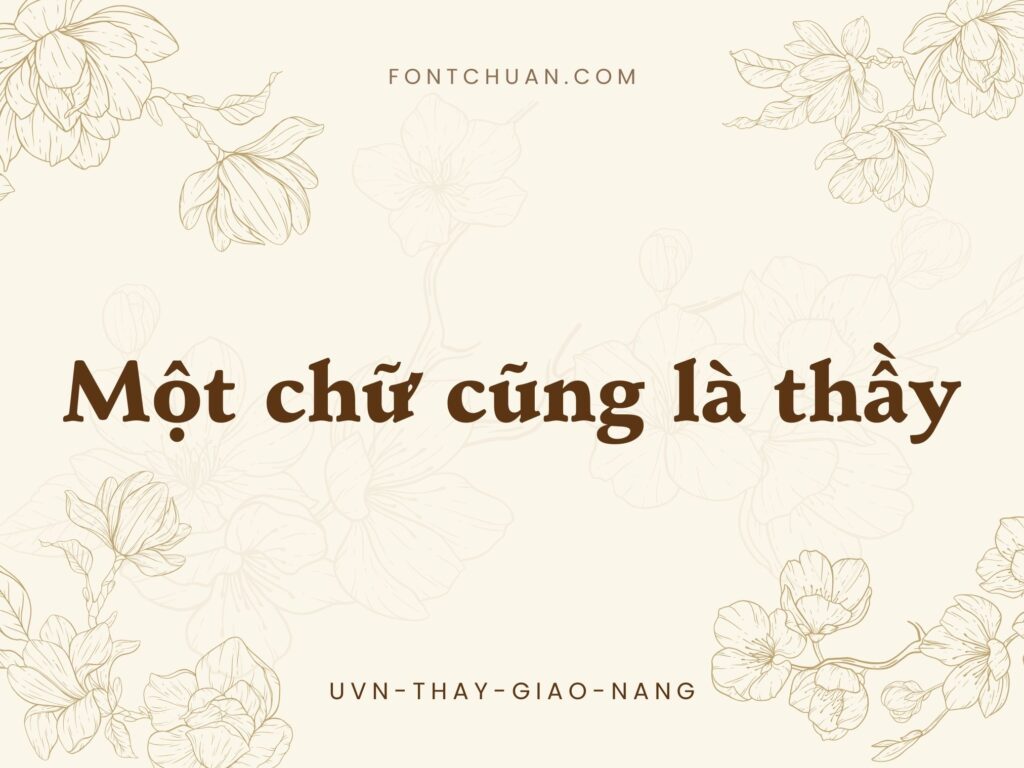
Font UVN Thay Giao Nang Việt Hóa
UVN Thầy Giáo Nặng là phiên bản chữ đậm của bộ font UVN Thầy Giáo, mang phong cách serif truyền thống với thiết kế mạnh mẽ, rõ ràng và giàu tính học thuật. Font này chỉ được sưu tầm và đăng bởi thành viên của Font Chuẩn.
UVN Thầy Giáo Nặng có cấu trúc chữ với các nét dày, chân chữ vững chắc, phù hợp cho các ứng dụng như thiết kế tiêu đề sách, bìa giáo trình, biển hiệu hoặc các ấn phẩm in ấn đề cao sự trang trọng và dễ nhận diện. Các ngành nghề như giáo dục, quảng cáo, công nghệ và bất động sản hoàn toàn có thể sử dụng font này để truyền tải nội dung một cách nổi bật và chuyên nghiệp.